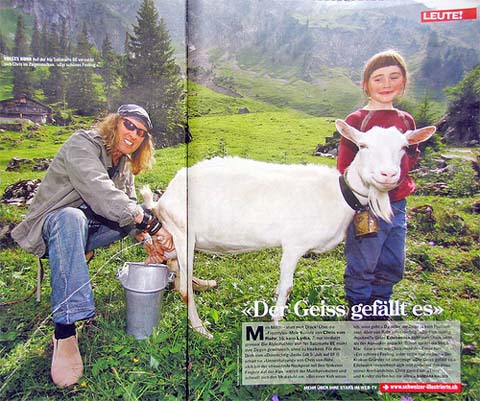
Revistas e magazines: introduçãoNo magazine processa-se o câmbio do textual para o visual. Ultrapassando a Tipografia do livro, interessada na elegância e na legibilidade dos tipos, a revista ilustrada traz novos impulsos ao typeface design.
O design de revistas e magazines é uma das área do design gráfico que mais impacto tem tido na Tipografia. As revistas têm sido o lugar de desenvolvimento de novos vocabulários de design, bem como de processos técnicos. Os leitores formam um elo emocional com os seus títulos favoritos, quer pelo seu conteúdo, quer pelo modo como se apresentam. "Compared to books," diz o autor Horst Moser, "magazine design is more flexible, often more elaborate, more expensive, and more experimental. Photography, typography and illustration all work together." Entre os principais formadores do design da revista moderna temos Alexey Brodovich e Paul Rand, e os designers mais importantes no processo de desconstrução da revista contemporânea foram Brody e David Carson. Desde que, a partir de meados do século XIX, os avanços tecnológicos aceleraram a Imprensa, as revistas têm desempenhado um papel significativo na vida diária de pessoas em todos os sectores da sociedade. O que é uma revista?Coloque-se perante uma banca de revistas em qualquer parte do mundo e à sua frente encontrar-se-á uma exibição espantosa - centenas de capas competindo pela sua atenção, cada uma delas tentando atraí-lo com as promessas daquilo que contêm... Muitas ostentam um nome familiar: Vogue, CQ, Sports llustrated, Piayboy, National Geographic, Time, Newsweek, Life, The Economist. É destas marcas internacionais que a maioria das pessoas se lembra quando pensa em revistas. Tais revistas mensais e semanários são os membros mais visíveis e mais conhecidos do mundo dos periódicos. Os públicosMas para além destas e muitas vezes fora das bancas, um grande número de títulos menos conhecidos títulos de comércio, suplementos de jornais, revistas para clientes, fãs e, hoje em dia, revistas na Internet (Webzines) , existem aos milhares, fornecendo informação aos leitores com interesses específicos, quer pessoais, quer profissionais. Onde quer que exista um grupo de pessoas interessado num determinado assunto, e um indivíduo ou organização com motivação suficiente para com ele comunicar, existe uma revista que estabelece a ponte entre ambos. A palavra magazine tem origem na língua árabe na qual significa armazém. As revistas que lemos são essencialmente uma colecção de diversos elementos - artigos e fotografias - unidos por um traço comum. As revistas e magazines fornecem informação a todas as profissões, interesses, hobbies ...e fantasias. Após um século de popularidade crescente, muitos «especialistas» fizeram a previsão que a televisão acabaria com as revistas e com os jornais. Em vez de desaparecerem, as revistas adaptaram-se e o número publicado hoje excede em muito o publicado aquando da introdução da televisão. Milhões de pessoas em todo o mundo recorrem hoje à World Wide Web procurando informação e entretimento e novamente as revistas multiplicam-se! Não só as revistas generalistas, mas especialmente as revistas vocacionadas a toda a espécie de nichos special interests não param de crescer e aumentar. A importância da fotografia nas revistas ilustradasEmbora registro estático sem o apelo das imagens em movimento que o cinema propões, as fotografias de estrelas, actrizes e VIPs publicadas pelas revistas ilustradas movimentavam o mercado editorial. Entre 1920 e 1930, Siegfried Kracauer, nas suas colunas semanais no jornal Frankfurter Zeitung, analisou o teor desse género de revistas:
Quem produz as revistas? E como?Sendo as revistas compostas por elementos diversos, elas são compiladas por uma variedade de pessoas cujas profissões, apesar de distintas e diferentes, se sobrepõem em várias áreas. Embora a maioria das revistas resulte de esforços de colaboração, existem meios hierárquicos onde é dada grande importância ao título pelo qual se exerce a profissão: editor, sub-editor, editor assistente, editor delegado, "features editor" (editor de configuração), editor colaborador, "editor-at-large" (editor geral/livre), director editorial - as variações são quase infinitas e quase infinitos os significados que envolvem. O status atribuído a um particular título profissional e as responsabilidades a ele inerentes variam de publicação para publicação. Em algumas editoras a decisão sobre qual a imagem a utilizar na capa, por exemplo, é confiada inteiramente ao director de arte. Noutras, o editor também quererá dar a sua opinião. Noutras ainda a decisão será tomada a um nível mais alto - estará a cargo da direcção (talvez um publicador ou um director editorial responsável pela produção de toda a editora). O editor é o derradeiro responsável pelo conteúdo da revista e tem normalmente experiência jornalística. A tarefa do editor é estabelecer os parâmetros do conteúdo (decidir o que é e o que não é do interesse dos leitores), distribuir artigos, instruir os outros funcionários a tempo inteiro quanto à preparação da revista e assegurar-se de que os exemplares e imagens entregues pelos colaboradores têm um nível suficientemente elevado para serem publicados. Aqueles que trabalham abaixo do editor têm uma variedade de designações que são imprecisas no seu significado - assistente de edição, jornalista, repórter, "feature writer", escritor sénior, correspondente, sub-editor, editor de informação, "feature editor" (editor de configuração), editor associado, editor delegado, editor colaborador e redactor livre são tudo títulos que surgem frequentemente nas fichas técnicas das revistas. Na sua maioria estes títulos dão alguma indicação da extensão da responsabilidade delegada pelo editor nos seus titulares: o "feature editor" (editor de configuração), por exemplo, terá particular responsabilidade em fornecer "feature ideas" (ideias base) e em lidar com os "feature writers". Os correspondentes, editores colaboradores e redactores têm normalmente um acordo com a revista pelo qual o seu conhecimento e experiência estão à disposição, sempre que necessário, dos funcionários regulares daquela, não estando eles próprios empregues a tempo inteiro o que lhes permite prosseguir outros interesses tais como escrever para outras revistas. O sub-editor é responsável pela revisão de provas da revista, procurando incoerências estilísticas ou factuais bem como erros ortográficos ou gramaticais. Pode também escrever os cabeçalhos, primeiras páginas, legendas, reescrever exemplares mal preparados e até dispor as páginas. Além destes colaboradores a tempo inteiro ou parcial que normalmente trabalharão na própria editora no escritório do publicador, as revistas muitas vezes empregam jornalistas independentes quer por serem especialistas quer porque não têm trabalho suficiente para empregar um escritor a tempo inteiro. A supervisão da compilação da revista é muitas vezes a tarefa de um director de produção ou de um editor de produção, cuja responsabilidade é a de se assegurar de que todo o conteúdo editorial e publicitário está presente e correctamente reunido, projectado, revisto e impresso. É o director de produção, após prévia consulta do editor e publicador, quem fixa os prazos de produção: determinando quando é que os exemplares e as cópias serão recebidos, que tempo levarão os processos de substituição e de design, e quando é que a revista precisa de ser impressa de modo a estar nas lojas a tempo. O designer editorial / director de arteO designer tem de dar «identidade» expressão e personalidade às diversas componentes para que estas possam ser reconhecidas como um todo coerente e original, atraindo o leitor num primeiro momento e depois construindo a fidelidade da marca. Os elementos têm de ser organizados de tal modo que o leitor possa encontrar rapidamente os items individuais nos quais está interessado. Estamos a falar da hierarquia dos conteúdos. A principal tarefa de um director de arte ou designer editorial é apresentar, num estilo gráfico próprio e original, o material que foi pedido pelos editores e fornecido pelos jornalistas, fotógrafos e ilustradores, mantendo os prazos projectados pelo director de produção. No sentido exacto da palavra, não existe diferença entre as tarefas desempenhadas sob o título de director de arte ou designer, com a excepção de que um director de arte ou um editor de arte terão ocasionalmente um ou vários designers trabalhando com eles e que são quem verdadeiramente dispõe as páginas concebidas e desenhadas pelo director de arte. O designer de uma revista, o seu director de arte, desempenha várias funções que têm de coexistir harmoniosamente se se pretende que a revista funcione como um todo. Estas tornam a revista mais apelativa para os seus leitores, dão-lhes uma personalidade ou identidade distintiva, e apresentam os conteúdos de modo a que os leitores achem útil na "navegação" através da revista. As relações laborais nas revistas são de extrema importância ja que os melhores resultados só serão atingíveis se o Design e Produção cooperarem ao longo de todo o processo com vista à produção de um produto final coerente. Um artigo terá um melhor impacto se o director de arte encarregue da fotografia compreender bem aquilo que o editor encarregou o jornalista de escrever. Na maioria das revistas o apertado prazo que se tem para fazer a sua compilação antes da publicação significa que não há espaço para erros. Uma boa comunicação e hábitos de trabalho firmes são essenciais. Onde são feitas as revistas?A imagem de uma sala de informação num jornal é - nos familiar devido à televisão e aos filmes: um espaço grande e amplo; um centro de grande actividade com centenas ou dezenas de ' pessoas correndo para cá e para lá. No entanto, com a informatização da maioria dos jornais nos últimos dez anos, e o aparecimento do e-mail, os jornais de hoje empregam menos pessoas em todas as áreas, incluindo na sala de informação, e o ruído das máquinas de escrever e dos gravadores tirando notas, já não paira no ar. As revistas semanais ou mensais empregam menos pessoal do que os jornais, e, com prazos limite mais longos, o ritmo é muitas vezes mais lento. Como as revistas são hoje produzidas por DTP, uma revista pode ser tecnicamente produzida por um único indivíduo num único computador. A tecnologia tornou a produção de uma revista num negócio geograficamente flexível: a adopção generalizada de e-mail e sistemas de edição digital permitiram que as companhias independentes de design se oferecessem com sucesso para a tarefa de direcção de arte nas revistas numa base mensal. BibliografiaFoges, Chris (Ed.). (1999). Magazine Design. RotoVision (avail. through Watson-Guptill). Owen, William. (1991). Modern Magazine Design. New York: Rizzoli. Heller, Steven, & Fili, Louise. (1996). Cover Story: The Art of American Magazine covers 1900-1950. San Francisco: Chronicle. Heller, Steven, & Pomeroy, Karen. (1997). Design Literacy: Understanding Graphic Design. New York: Allworth Press. Johnson, Sammye, & Prijatel, Patricia. (2000). Magazine Publishing. Lincolnwood, IL: NTC/Contemporary. King, Stacey. (2001). Magazine Design that Works. Rockport. Leslie, Jeremy, & Blackwell, Lewis. (2000). Issues: New Magazine Design. Corte Madera, CA: Gingko Press. Kery, Patricia Frantz. (1982). Great Magazine Covers of the World. New York: Abbeville Press. Pedersen, B. Martin. (1997). Graphis Magazine Design 1. New York: Graphis. Remington, R. Roger, & Hodik, Bargara J. (1989). Nine Pioneers in American Graphic Design. Cambridge, MA: The M.I.T. Press. |